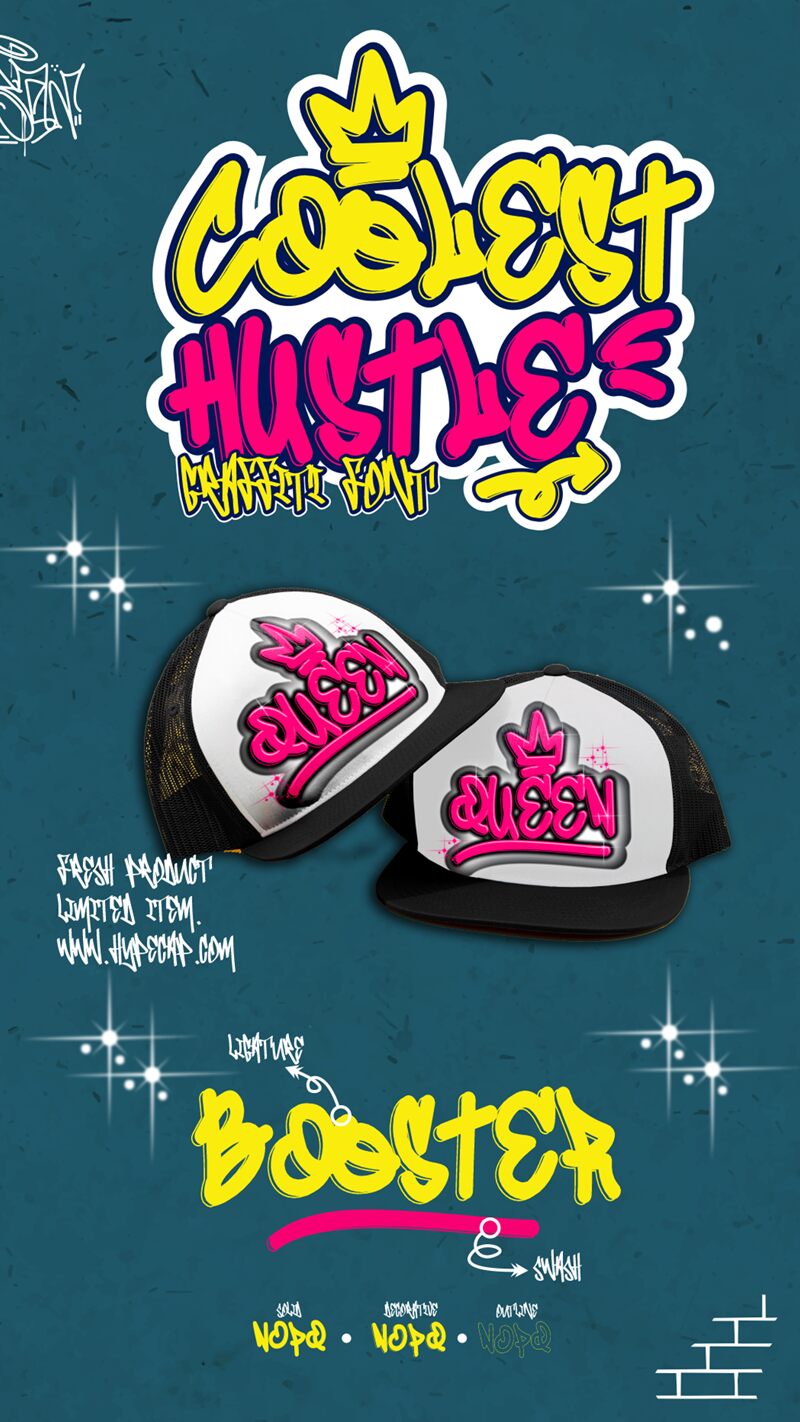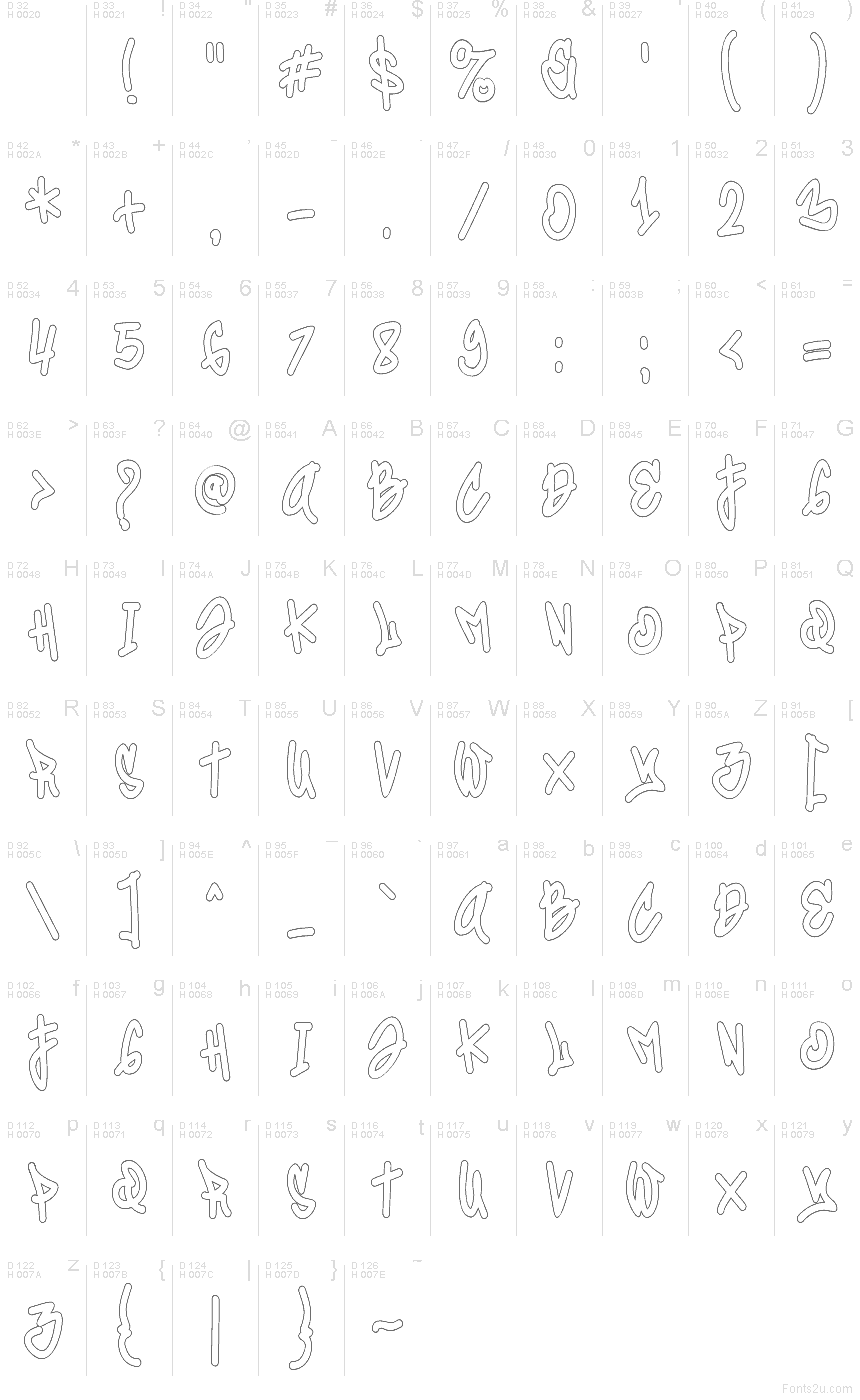
Font Coolest Hustle Outline od Muhammada Panji Ramdhaniho ze studia Sipanji x Figuree přináší skicovitou, ručně kreslenou energii, která vypadá jako čerstvé tahy fixou na zdi. Jako součást rodiny Coolest Hustle je to bezplatné graffiti písmo, jehož vzdušný obrys zachovává potřebný postoj, aniž by se váš layout proměnil v černou skvrnu. Vysoké, dynamické tvary písmen a jemné vlnky dodávají každému slovu hravý rytmus, jako by bylo nastříkáno jedním sebevědomým tahem.
Použijte Coolest Hustle Outline pro dodání řízu logům streetwearu, dropům tenisek, titulkům na plakátech, obalům alb, náhledům videí na YouTube, letákům na akce nebo sadám samolepek. Toto bezplatné písmo skvěle vynikne i v reklamách na sociálních sítích a na merchi, kde chcete mít šmrnc, ale potřebujete, aby sdělení bylo čitelné na první pohled. Pro hlavní text ho zkombinujte s čistým geometrickým bezpatkovým písmem a nechte obrys dýchat – mírně zvětšené titulky vypadají obzvlášť ostře.